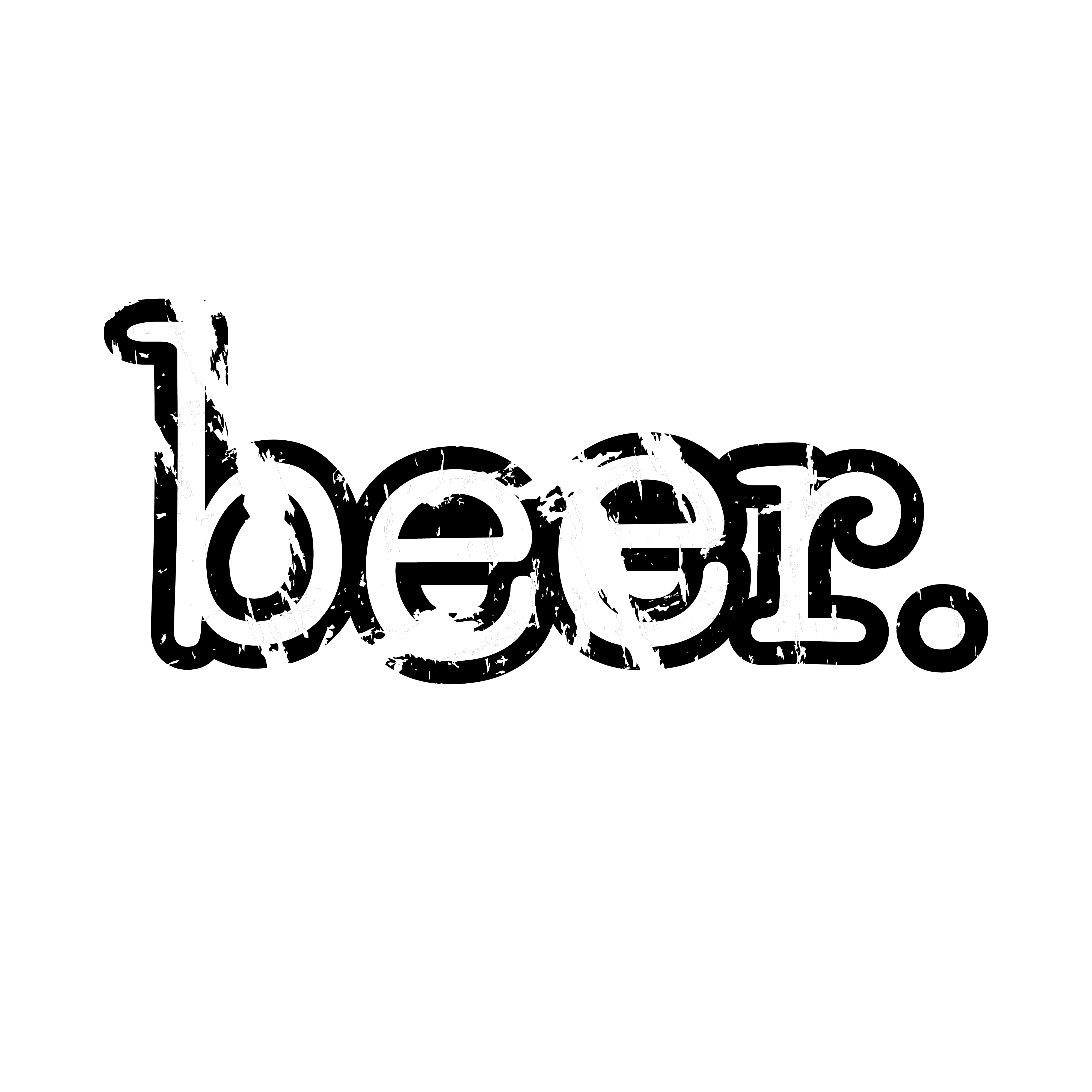
Beer Money
Шрифты — это как краска на феррари, как элегантное платье на соблазнительной красотке.
Согласись, если ты увидишь феррари покрашенную валиком, вместо восторга у тебя останется отпечаток ладони на лице от фейспалма. Да, это по-прежнему будет феррари, но в голове скорее всего промелькнет: «Пи#дец…». Тоже самое, если одеть принцессу в лохмотья и измазать углем. Этот же принцип действует и с твоим текстом.
ШРИФТЫ — поддерживают и во многом определяют эмоцию твоей писанины.
Мы не будем углубляться в профессиональные детали. Знать какие шрифты относятся к «Брусковой антикве», а какие к «Нео-гротеску», тебе абсолютно ни к чему. Это безусловно важно и помогает вызвать эмоцию более точно и глубже. Об этих деталях я расскажу в приватных темах.
Каждый шрифт несет в себе какую-то эмоцию. Чаще всего используют шрифт с нейтральной эмоцией. Как правило, в тех случаях, когда ЦА сильно размыта, или писюк не удосужился узнать свою аудиторию. В прочем, чтобы не грузить твой мозг, я взял нейтральную фразу и обыграл ее разными шрифтами.
Шрифт: Beer Money
Такое ощущение, что вот-вот воткнут ножик промеж лопаток или влупят чем-нибудь тяжелым по голове. Неприятная эмоция. Страх, агрессия, опасность.
Шрифт: MADE The Artist Script
В этом случае эмоция прямо противоположная. Как будто безнадежный романтик доверил ветру передать сообщение своей возлюбленной. Самые явные эмоции считываемые с этого шрифта: романтизм, нежность и легкость.
Как тебе? Более чем наглядно. «Ник, с этим понятно. Но большой объем текста такими шрифтами неудобно читать.
» — заметит вдумчивый читатель. Ты совершенно и абсолютно прав, мой хороший. Эти шрифты относятся к категории «Акцидентный». Из названия уже можно понять, что такими шрифтами расставляют АКЦЕНТЫ в тексте. Это короткие предложения в два, тире, пять слов. Такие шрифты используют когда нужно вызвать сильную эмоцию.
У нас в рунете со шрифтами беда, точнее с их подбором. Мало кто впаривается в тему и доводит свои месседжи до совершенств. В основной массе писак преобладает правило — «И так сойдет!». Но ты, читаешь этот канал не ради того, чтобы пополнить ряды говнокоперов, ты хочешь быть на несколько порядков выше и эффективней. Правда?
Поэтому, для того, что бы усилить свой текст применяй простые правила:
- Не более трех шрифтов на один сайт или лонгрид. В идеале два. Даже есть такое понятие как шрифтовая пара.
Специально для новичков создана масса ресурсов по подбору шрифтов. Ресурсы легко гуглятся по запросу — «Подобрать шрифтовую пару». - Шрифт легко читается. Буквы различимы и не приходится догадываться, что написано. Проверить это можно мелким текстом. Если шрифт 8-9 пикселей читаем — шрифт подходит.
- Обращайся к своим чувствам. Прислушайся к ощущениям. Поддерживает ли шрифт эмоцию, которую ты передаешь в тексте? Нравятся ли тебе сочетание пары? Не вызывает ли эмоциональный диссонанс если на текст посмотреть издалека?
- Следуй правилам типографики. Подробнее о типографике мы поговорим в другом посте. Пока обращай внимание на межстрочный интервал. Он должен быть 1,3 – 1,5 строки. Расстояние между абзацами, чтобы абзац выглядел как блок. И расстояние сверху заголовка больше, чем снизу. Пока достаточно.
- Избегай шрифтов: Arial и Comics Sans.